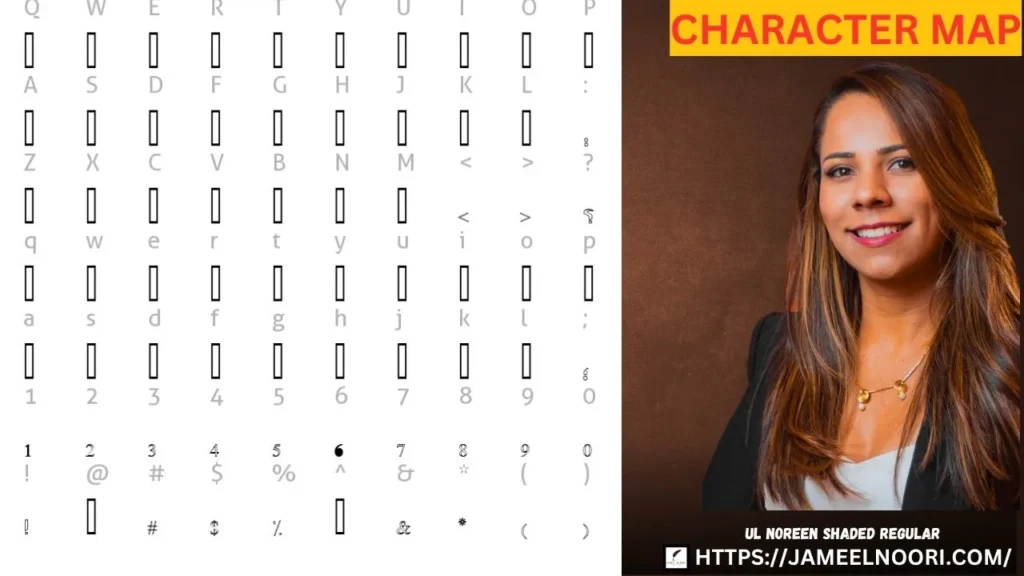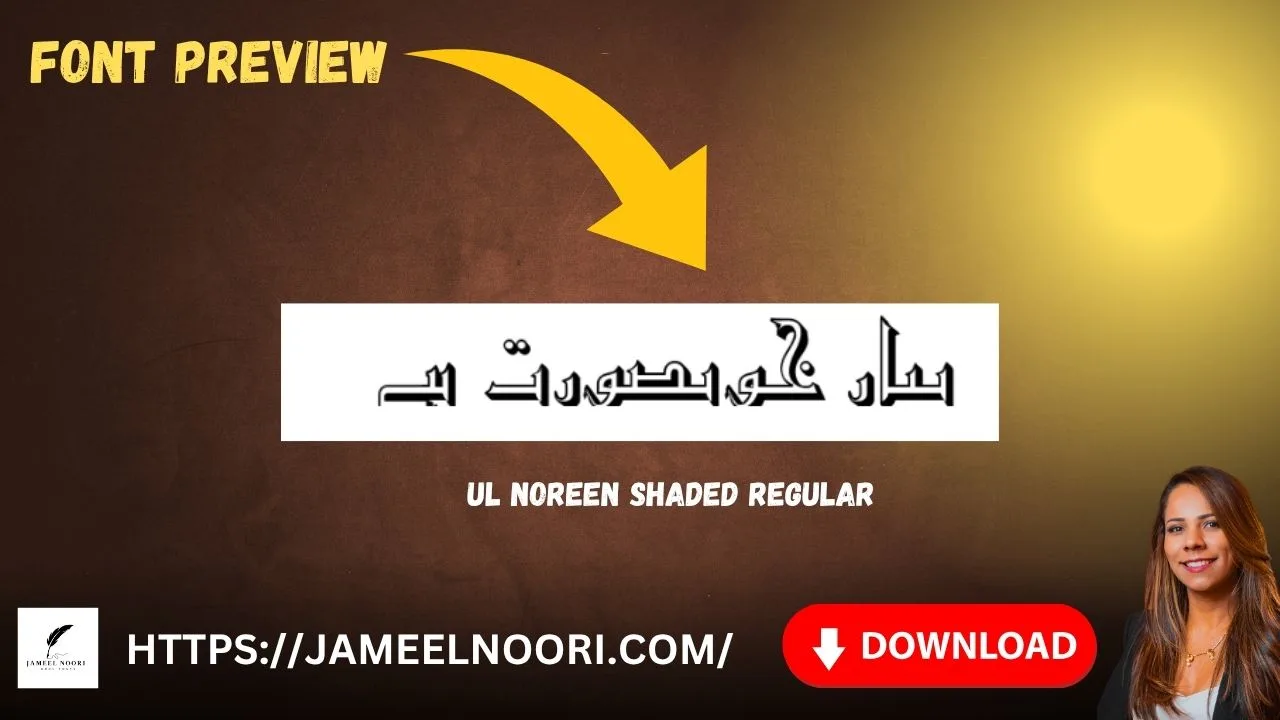
UL Noreen Shaded Regular Font ek popular TrueType font hai jo Urdu typography lovers ke liye perfect choice hai. Is font ko ab tak 543,251 downloads mil chuke hain aur 312 users ne 4.83/5 rating di hai. Is article me hum apko is font ke bare me complete information dy gy taki aap bina time waste kiye is font ka best use kar saken.
Features of UL Noreen Shaded Regular Font
| Feature | Description |
| Style | Regular Shaded |
Key Points:
- Ideal for websites and digital content
Why Choose UL Noreen Shaded Regular Font?
UL Noreen Shaded Regular Font ki khasiyat ye hai ke ye modern aur stylish look provide karta hai, jo Urdu blogs, websites, aur graphic designs ke liye ideal hai. Is font ke unique shaded design ki wajah se text zyada attractive aur readable lagta hai.
Benefits include:
- Stylish Urdu typography
- High readability aur professional look
Best Uses of UL Noreen Shaded Regular Urdu Font
UL Noreen Shaded Regular Font versatile hai aur multiple purposes ke liye use ho sakta hai:
- Urdu blogging aur websites
- Social media posts
- Graphic designing aur posters
- Digital publications
Pro Tip: Combine shaded fonts with simple headings for maximum readability.
Comparison With Other Urdu Fonts
| Font | Style | Popularity | Rating |
| UL Noreen Shaded Regular | 543,251 | 4.83 |
Observation: UL Noreen Shaded Regular font zyada stylish aur modern feel deta hai aur professional projects me preferred hai.
UL Noreen Shaded Regular Font ek stylish, readable, aur professional Urdu font hai jo designers aur bloggers ke liye perfect hai. Iska shaded design aur TrueType format content ko attractive aur user-friendly banata hai. Is article me hum apko is font ke bare me complete information dy gy taki aap bina time waste kiye is font ka best use kar saken.
Can it be used in graphic design?
Absolutely, it’s ideal for posters, logos, and social media designs.
Does it support all Urdu characters?
Yes, it includes a complete Urdu character set.
Can I combine it with other fonts?
Yes, it pairs well with simple and modern fonts for best readability.